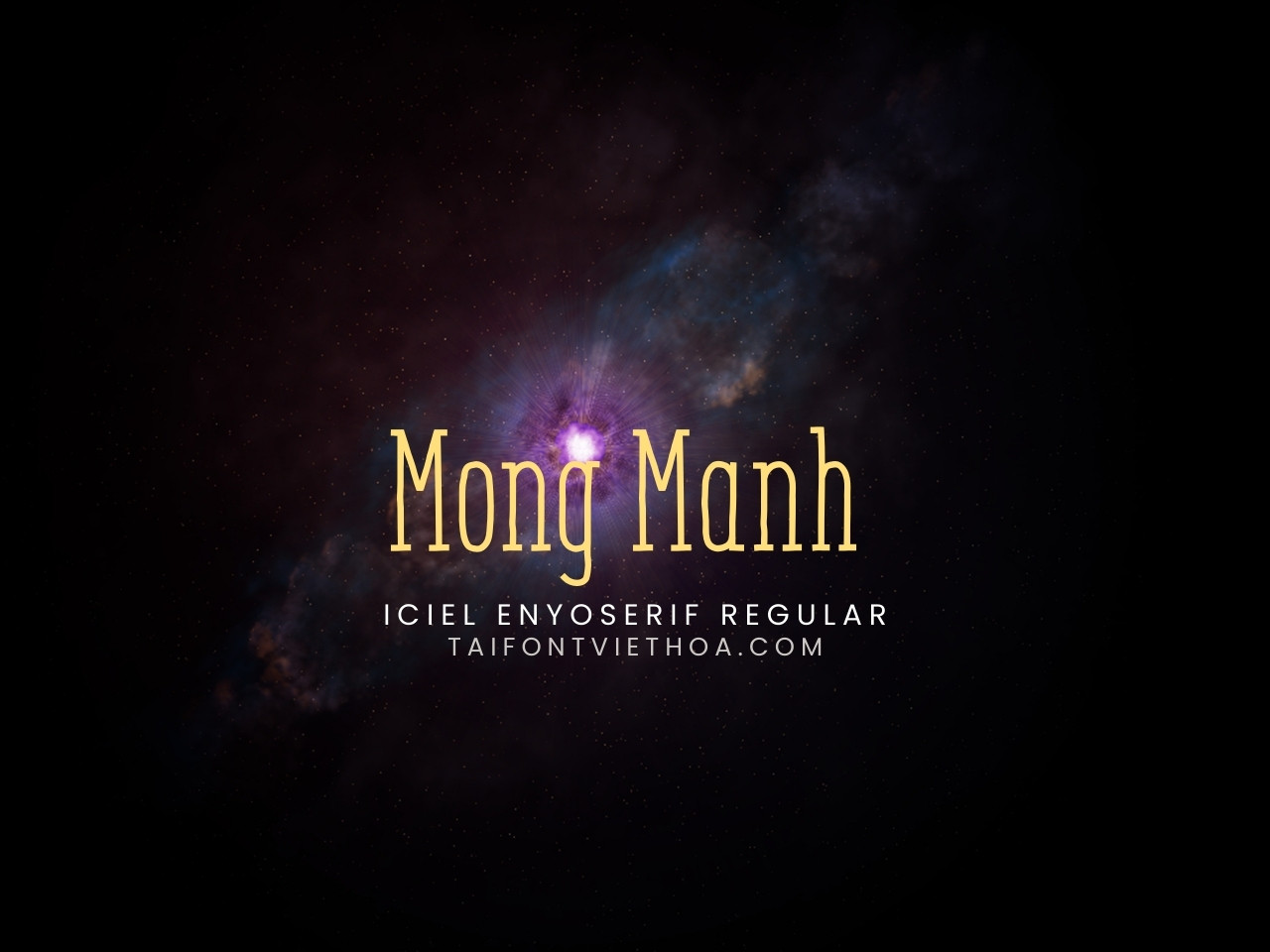
Giới thiệu về font iCiel Enyo – Phong cách cổ điển, nữ tính và thanh lịch
iCiel Enyo là một kiểu chữ serif trang trí (decorative serif) được thiết kế với cảm hứng từ những phong cách cổ điển pha lẫn hiện đại. Font sở hữu các đường nét mảnh, kết cấu hài hòa và hình dáng chữ được tạo hình duyên dáng, giúp tạo nên một diện mạo sang trọng, bay bổng và nữ tính. Phiên bản Việt hóa được thực hiện bởi iCiel, hỗ trợ đầy đủ tiếng Việt cùng hơn 60 ngôn ngữ khác, giúp dễ dàng sử dụng trong các thiết kế dành cho thị trường đa ngôn ngữ.
Font được taifontviethoa.com tuyển chọn và giới thiệu như một giải pháp typography lý tưởng cho các thiết kế đậm chất nghệ thuật, giàu thẩm mỹ, từ thiệp mời, bìa sách, bao bì sản phẩm đến logo thương hiệu thời trang, mỹ phẩm hoặc ấn phẩm quảng bá mang màu sắc nhẹ nhàng, nữ tính. Enyo không chỉ là một font chữ, mà còn là sự kết hợp tinh tế giữa cổ điển và hiện đại trong từng đường nét.
Đặc điểm thiết kế và ứng dụng nổi bật của font iCiel Enyo
iCiel Enyo thuộc nhóm serif trang trí, với nét chữ mảnh mai, phần chân chữ được kéo dài thanh thoát, uốn lượn nhẹ ở một số ký tự để tăng tính duyên dáng. Thiết kế font mang lại cảm giác cao cấp, thời thượng và rất hợp thị hiếu thiết kế nữ giới. Ngoài ra, các chi tiết như ligatures và alternate glyphs giúp font linh hoạt hơn trong trình bày và bố cục typography chuyên nghiệp.
Font phù hợp với các ngành nghề như thời trang nữ, mỹ phẩm cao cấp, spa – làm đẹp, thiệp cưới, ẩm thực và các thương hiệu lifestyle cao cấp. Ứng dụng tiêu biểu gồm: logo thương hiệu thời trang, typography poster, tiêu đề bìa sách, bao bì mỹ phẩm, thiết kế social media hoặc thiệp mời sự kiện sang trọng như lễ cưới, trung thu, sinh nhật.